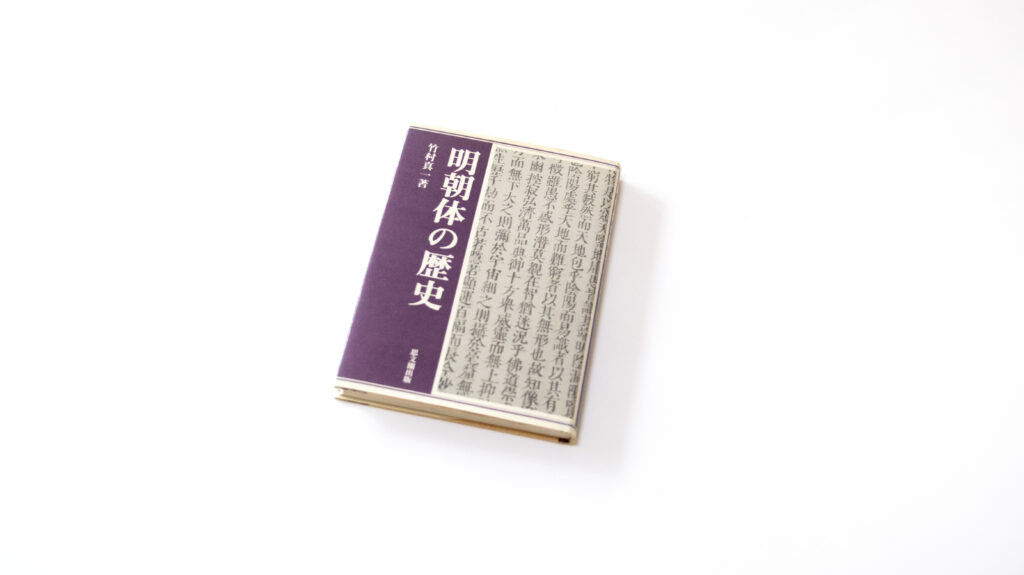
今回は、竹村真一著の『明朝体の歴史』を紹介します。
本書は紙や布についてや印刷の起源から始まり、文字や書体の変遷、中国での明朝体の発生にいたるまでの経緯、そして日本に伝わって定着するまでの過程がまとめられています。
楷書が変形してどのように明朝体になっていったかについての章では、版下となる書かれた文字と書いた人に対する気持ちや、書道的な持ち味を捨てられずに残った楷書の筆跡が明朝体の読みやすい形として抽象化されていったという記述は、明朝体にいたるまでの形が文字の彫りやすさ、分業化、能率の向上のみではない変遷の仕方が興味深かったです。
明朝体の形の変化が追えるような、経典などの版本の図版も多く載っています。
それらの明朝体のウロコについて分類された表は、現代で目にしている三角形とは異なって上に高くはねあげているものなど形にバリエーションがあり面白く、筆の運びや流れからきているものだと改めて感じました。
画期をなした書体がどのような変遷を経て様式化され定着するに至ったか。書体デザインに携わる者にとって興味の尽きないテーマである。残念なことに書体の移り変わりを丁寧に読み解いた本は少ない。その意味で『明朝体の歴史』は貴重な一冊といえよう。加えて『文字の文化史』は、概説書ではあるものの、道具および素材の視点から漢字書体の変遷を把握するのに適している。